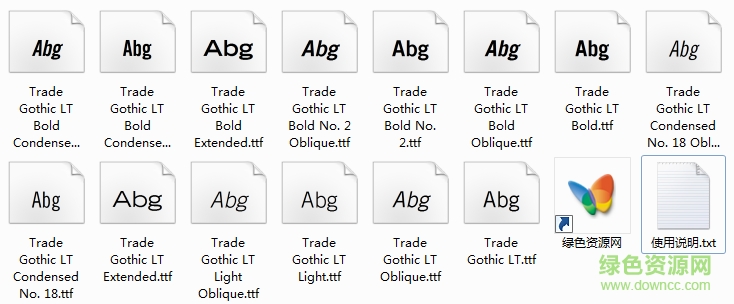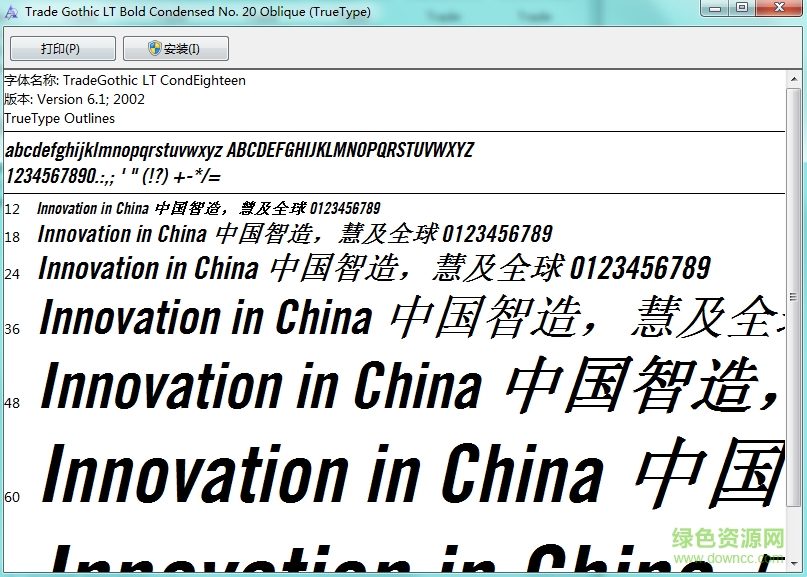
TradeGothic是一款擁有14款書法格式的系列字體,包括不同加粗、大小、亮度等,本字體清晰大氣,有著端正的筆型和舒適的觀賞美感,歡迎有需要的朋友來綠色資源網(wǎng)免費(fèi)下載!
TradeGothic是無襯線體字體家族系列字體,包括Trade Gothic LT、Trade Gothic LT Oblique、Trade Gothic LT Light Oblique、Trade Gothic LT Extended、Trade Gothic LT Condensed No. 18、Trade Gothic LT Condensed No. 18 Oblique、Trade Gothic LT Bold、Trade Gothic LT Bold Oblique、Trade Gothic LT Bold No. 2、Trade Gothic LT Bold No. 2 Oblique、Trade Gothic LT Bold Extended、Trade Gothic LT Bold Condensed No. 20、Trade Gothic LT Bold Condensed No. 20 Oblique等14款字體。